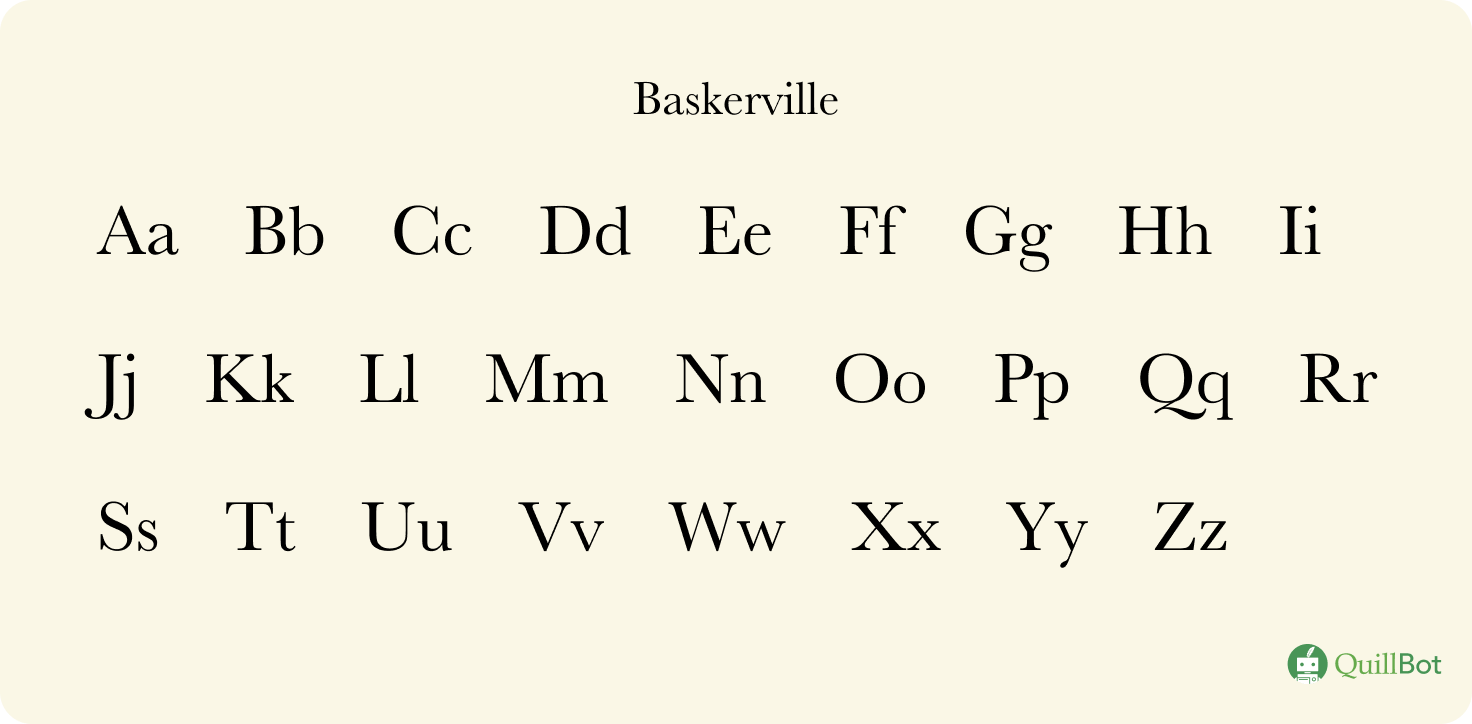
Baskerville (police de caractères)
En matière d’ouvrages littéraires, le contenu est évidemment central, puisqu’il donne sa raison d’être au livre. Pourtant, tous les lecteurs passionnés vous le diront, on aurait tort de négliger l’importance capitale du contenant.
Couverture attrayante, embossages savamment choisis, reliures artisanales ou encore grammage du papier sont autant de paramètres qui pèsent lourd dans la balance au moment de concevoir l’objet livre, tout comme le choix de la police d’écriture dédiée au corps du texte.
Parmi les classiques en la matière, on retrouve les emblématiques Times New Roman, Garamond et Palatino, sans oublier Baskerville, qui conjugue sobriété et raffinement comme aucune autre.
- Année de création : 1757
- Pays de création : Angleterre
- Créateur : John Baskerville (imprimeur et typographe)
- Commercialisation : par la Fonderie G. Peignot & Fils
- Type de police : Classique
- Type d’empattement : Avec empattement (serif en anglais)
- Classification Vox-Atypi : Réale
- Popularité : ++ (utilisée essentiellement pour l’édition de livres)
- Image véhiculée : Élégante, classique, raffinée, littéraire, confortable à la lecture.
- Point d’attention particulier : Police dont la conception remonte à plusieurs siècles.
Produire des livres plus nets, plus raffinés que ce qui se faisait jusqu’alors ; telle fut l’ambition à l’origine de la police Baskerville, qui porte encore à ce jour le nom de son créateur.
Le pari a non seulement été remporté haut la main, mais la réputation de Baskerville, née au milieu du XVIIIe siècle, a résisté à l’épreuve du temps. Aujourd’hui encore, elle apporte aux textes qu’elle habille une touche de clarté et de distinction, sans jamais sembler désuète.
Attention toutefois : une telle légende de la typographie mérite d’être utilisée à bon escient, et surtout dans le bon contexte, afin de ne pas envoyer le mauvais message.
Police Baskerville : histoire et commercialisation
Baskerville peut se targuer d’être l’une des polices d’écriture les plus anciennes parmi celles que l’on utilise encore en masse dans les années 2020.
En effet, contrairement à la plupart des polices de caractère qui tiennent le haut du pavé, Baskerville n’est pas née au XXe siècle, mais au XVIIIe.
L’idée conductrice est alors la suivante : créer une police qui permette une impression à grande échelle et optimisée pour la lecture des textes au long cours.
Deux critères essentiels sont alors priorisés :
- des lignes, des courbures et des empattements nets (pour se défaire de cette impression que l’encre « bave » légèrement sur le papier, courante avec les polices dites Old Style à l’époque),
- un rendu raffiné.
Pour ce faire, le créateur de Baskerville, John Baskerville (1706-1775), cherche à produire un haut contraste global, à un niveau inédit jusqu’alors.
Mais à la lumière du nom du créateur de cette police (« Baskerville », un nom finalement pas si rare que ça en Angleterre), on devine qu’il n’en est rien, et que l’artiste a tout simplement signé son nom de son patronyme.
Et s’il fallait encore un argument pour vous convaincre qu’il n’existe aucun lien entre les deux, sachez que le Chien des Baskerville a été publié pour la première fois en 1902… soit 145 ans après la naissance de la police Baskerville.
Sous l’impulsion de John Baskerville et de ses équipes, la fameuse police voit le jour en 1757.
Sa gravure dans le métal est confiée au graveur John Handy, et sa commercialisation assurée par la Fonderie G. Peignot & Fils, une fonderie française qui fait la fierté du patrimoine typographique tricolore.
Une légende est bel et bien née !
Baskerville, une police de transition
Avant toute chose, Baskerville est une police de caractères dite avec empattement.
Ce type de police s’oppose aux polices dites avec empattement, distinction que l’on opère selon un critère visuel immédiatement reconnaissable.
- Les polices serif (avec empattement en français) possèdent de petits « pieds », crochets ou traits décoratifs aux extrémités de leurs caractères.
Elles évoquent immédiatement un design classique, sérieux, et confèrent à la communication un caractère institutionnel symbolique d’une certaine autorité.
Elles sont aussi très utilisées dans l’édition et la presse écrite, car jugées plus adaptées à la lecture de textes sur le long court.
Exemples de polices avec empattement : Garamond, Palatino Linotype, Times New Roman…
- À l’inverse, les polices sans serif ne possèdent pas d’empattements. Leurs lignes sont droites et nettes.
Leur aspect est moderne et minimaliste ; leur design épuré, mais accessible.
On les utilise volontiers sur le web en raison de leur lisibilité optimisée pour les écrans et de leur côté « percutant ».
Exemples de polices sans empattement : Arial, Aptos, Calibri, Comic sans MS, Helvetica, Open Sans, Roboto, Tahoma…
Au XVIIIe siècle, les polices avec empattement ont déjà la cote dans l’édition de livres, notamment celles appartenant à la famille des Old Style.
Les polices de caractères de la famille des garaldes (qu’on appelle Old Style en anglais) se caractérisent par leurs empattements triangulaires et le contraste qu’elles présentent entre leurs pleins et leurs déliés. Historiquement, elles sont apparues à la Renaissance, soit vers la fin du XVe siècle.
Elles sont directement inspirées de la calligraphie antique et se distinguent par un aspect classique et chaleureux, bien que leurs lignes parfois épaisses aient tendance à mal vieillir et à s’adapter difficilement aux usages numériques de notre temps… Mais revenons pour le moment au XVIIIe siècle.
Les évolutions en matière d’imprimerie appellent justement l’invention de nouvelles polices avec empattement, encore plus contrastées que les garaldes, mais ne reniant aucunement leur héritage classique qui sied tant à la conception de livres.
Qu’à cela ne tienne : la famille des réales fait son apparition. Baskerville en est la première illustre représentante, mais elle sera rejointe (et même supplantée) par Times New Roman, qui est certainement la police à empattement la plus utilisée dans le monde depuis sa création.
Dans le jargon typographique, on qualifie de ce fait les polices appartenant au groupe des réales de polices de transition. Et Baskerville étant arrivée bien avant Times New Roman (née au XXe siècle), on la considère comme la police de transition par excellence.
Concrètement, Baskerville se distingue par ses formes amples et généreuses.
Elle présente un contraste particulièrement marqué entre pleins et déliés, des empattements horizontaux en bas de casse (que l’on appelle plus communément les minuscules dans le langage courant) et des hampes à la verticalité marquée.
Baskerville offre ainsi un vrai confort de lecture, accentué par un rythme régulier dans la succession des caractères.
En somme, il s’agit d’une police aussi commode et pratique qu’esthétique.
Pour pallier ce problème, les typographes contemporains ont travaillé sur plusieurs variations destinées à optimiser l’usage de Baskerville sur écran, dont Libre Baskerville.
Avec ses empattements plus larges, son contraste retravaillé et sa hauteur plus élevée, Libre Baskerville, pourtant basée sur la police originale, parfait la lecture numérique de pages web et d’articles mis en page à l’aide de cette légende de la typographie.
Cerise sur le gâteau : elle est libre de droits, et peut être téléchargée gratuitement en ligne.
Baskerville : quels usages en 2026 ?
Pour toutes les raisons et caractéristiques listées précédemment, Baskerville renvoie une impression de clarté et de rigueur, sans pour autant paraître trop sérieuse.
Elle est associée à une certaine tradition littéraire, et ne pose aucun problème quant à son usage dans des textes longs.
- l’édition de livres. Elle convient en particulier des livres de fiction et des classiques de la littérature, mais peut également s’accorder avec certains essais, philosophiques notamment,
- les articles de presse (sur papier ou en ligne) invitant à la réflexion intellectuelle,
- la construction d’identités visuelles sobres et humanistes (pour le logo d’une librairie, d’une bibliothèque ou d’un blog littéraire, ou encore pour un groupe de réflexion politique)…
À l’inverse, on aura tendance à éviter Baskerville pour :
- les contenus courts et/ou sans orientation intellectuelle, littéraire ou réflexive marquée,
- l’édition de livres pratiques,
- l’identité visuelle d’une marque qui se veut jeune, dynamique et résolument avant-gardiste,
- les projets à direction artistique ultra-minimaliste (Baskerville fait trop « habillée » pour cela)…
Baskerville : quelles alternatives ?
Baskerville a ses fans de la première heure, mais même pour les aficionados, un peu de changement peut être bienvenu…
Si tel est le cas pour vous et que vous recherchez des polices proches de Baskerville, aux morphologies voisines et provoquant des effets similaires sur votre audience, voici quelques propositions qui devraient vous parler :
- Bembo,
- Book Antiqua,
- Caslon,
- Charter,
- Crimson Text,
- Garamond,
- Georgia,
- Goudy Old Style,
- Minion Pro,